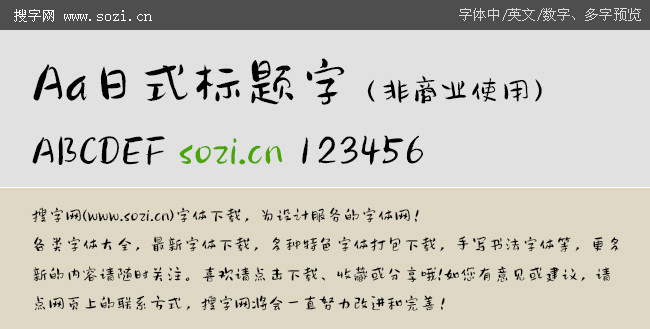
Aa日式標(biāo)題字(非商業(yè)使用)
搜字網(wǎng)給大家提供一款A(yù)a日式標(biāo)題字(非商業(yè)使用)中文字體下載,該字體線條粗細(xì)適中,字形偏日式風(fēng)格,俏皮可愛,適合包裝畫冊等兒童卡通宣傳廣告等應(yīng)用(此字體為個人非商用版,商用可以聯(lián)系QQ:1006760504)。